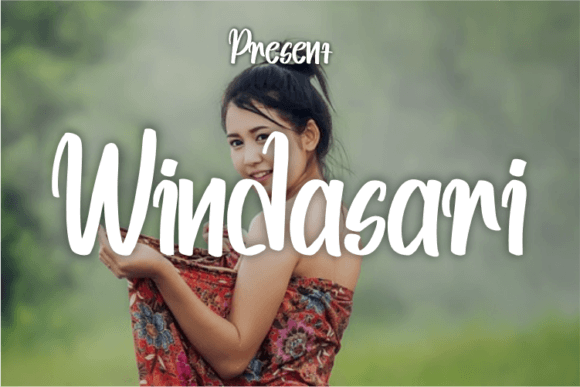
Windasari
إذا كنت تبحث عن أصول عالية الجودة مثل Windasari، فإن هذه الحزمة المميزة هي خيار رائع لمشاريعك الإبداعية.
تم تصميمه بدقة، ويوفر Windasari متجهات نظيفة وطباعة سلسة وترخيصًا تجاريًا لراحة بالك.
سواء كنت تقوم بإنشاء منتجات الطباعة عند الطلب أو دعوات الزفاف أو رسومات وسائل التواصل الاجتماعي، فإن Windasari هو الخيار المثالي.